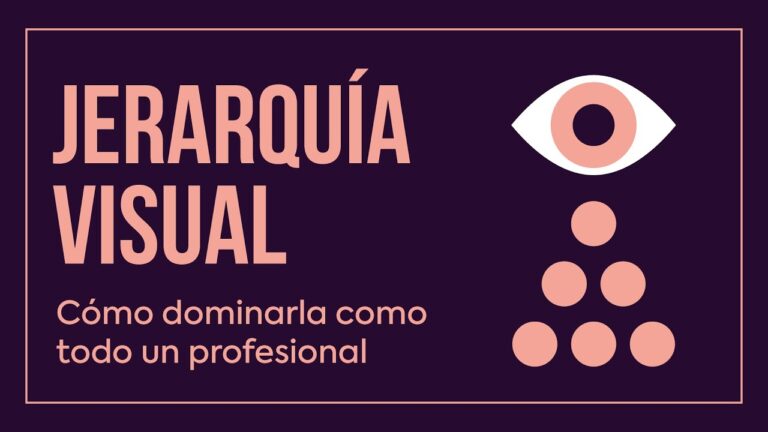
La importancia de la tipografía en la jerarquía visual
La tipografía juega un papel fundamental en la jerarquía visual de un diseño, ya que es capaz de captar la atención del lector, transmitir emociones y guiar la lectura de manera eficaz. En este artículo, exploraremos la importancia de elegir la tipografía adecuada para lograr un diseño visualmente impactante y coherente. ¡Descubre cómo la elección de fuentes puede marcar la diferencia en la comunicación visual!
¿Cuál es la jerarquía en la tipografía?
La jerarquía tipográfica es esencial en el diseño visual, ya que permite destacar la información clave y guiar la lectura de manera eficiente. Al utilizar diferentes elementos tipográficos como tamaños, pesos y colores, se logra crear un orden visual que mejora la legibilidad y la comprensión del contenido. Esta técnica es fundamental para captar la atención del espectador y transmitir el mensaje de forma clara y concisa.
¿Qué importancia tiene la tipografía en el diseño y la comunicación visual?
La importancia de la tipografía en el diseño y la comunicación visual es fundamental. No se trata solo de elegir fuentes, sino de influir en la forma en que se comunica y percibe un mensaje. Además, desempeña un papel crucial en la identidad de marca y es esencial para la usabilidad y la experiencia del usuario.
¿Por qué es importante jerarquizar los textos?
Jerarquizar los textos es de vital importancia para organizar el mensaje de manera clara y concisa. Esta estructura ayuda a captar la atención de los lectores de forma rápida y eficiente, guiándolos hacia la información más relevante y facilitando la comprensión del contenido en su totalidad.
El poder de la tipografía en el diseño
La tipografía es una herramienta poderosa en el diseño, capaz de transmitir emociones, personalidad y estilo. La elección de una fuente adecuada puede marcar la diferencia entre un diseño ordinario y uno extraordinario. Es importante considerar factores como el tamaño, el grosor y el espaciado de la tipografía para lograr un equilibrio visual y una buena legibilidad.
Además, la tipografía adecuada puede reforzar la jerarquía visual de un diseño, guiando al espectador a través de la información de manera intuitiva. Al jugar con diferentes estilos y tamaños de tipografía, es posible resaltar elementos clave y crear un impacto visual que capture la atención del público de manera efectiva. La tipografía también puede ayudar a establecer la identidad de una marca o proyecto, transmitiendo su esencia y valores de manera coherente.
En resumen, la tipografía es una herramienta versátil y creativa que puede potenciar el impacto visual de cualquier diseño. Desde la elección de una fuente adecuada hasta la combinación de estilos y tamaños, cada detalle tipográfico puede marcar la diferencia en la percepción y la comunicación de un mensaje. Por lo tanto, es fundamental valorar el poder de la tipografía en el diseño y aprovecharlo al máximo para crear piezas visuales memorables y efectivas.
Cómo la tipografía puede cambiarlo todo
La tipografía es una herramienta poderosa que puede cambiar por completo la apariencia y el impacto de un mensaje. Desde un elegante y sofisticado tipo de letra hasta una fuente audaz y llamativa, la elección de la tipografía puede transmitir emociones y personalidad, afectando la forma en que el público percibe y comprende la información. Un diseño bien pensado con la tipografía adecuada puede captar la atención, transmitir confianza y crear una experiencia visual memorable.
La importancia de la tipografía va más allá de la estética, ya que también puede influir en la legibilidad y la comprensión del contenido. El uso de una tipografía clara y legible puede hacer que la información sea más accesible y fácil de asimilar para el lector, mientras que una tipografía inadecuada puede dificultar la lectura y desviar la atención del mensaje. Por lo tanto, al considerar cómo la tipografía puede cambiarlo todo, es crucial seleccionar cuidadosamente las fuentes que mejor se adapten al propósito y al público objetivo, aprovechando su poder para mejorar la comunicación visual.
Secretos para una jerarquía visual efectiva
Descubre cómo utilizar el contraste de colores para crear una jerarquía visual efectiva en tus diseños. Al combinar colores brillantes con tonos neutros, podrás resaltar la información más importante y guiar la mirada del espectador de manera sutil pero impactante. ¡Atrévete a jugar con la paleta cromática y sorprende con tus composiciones!